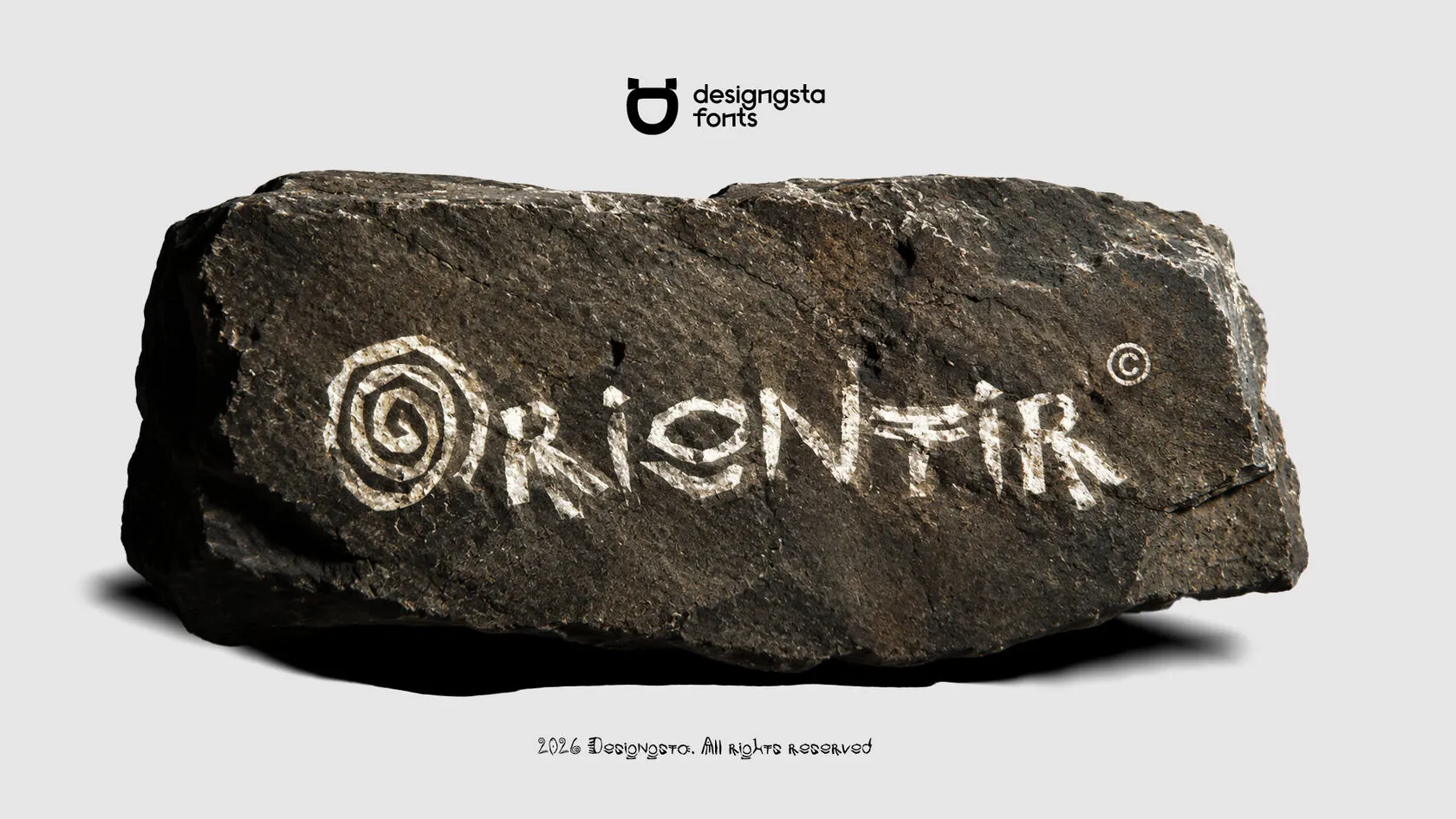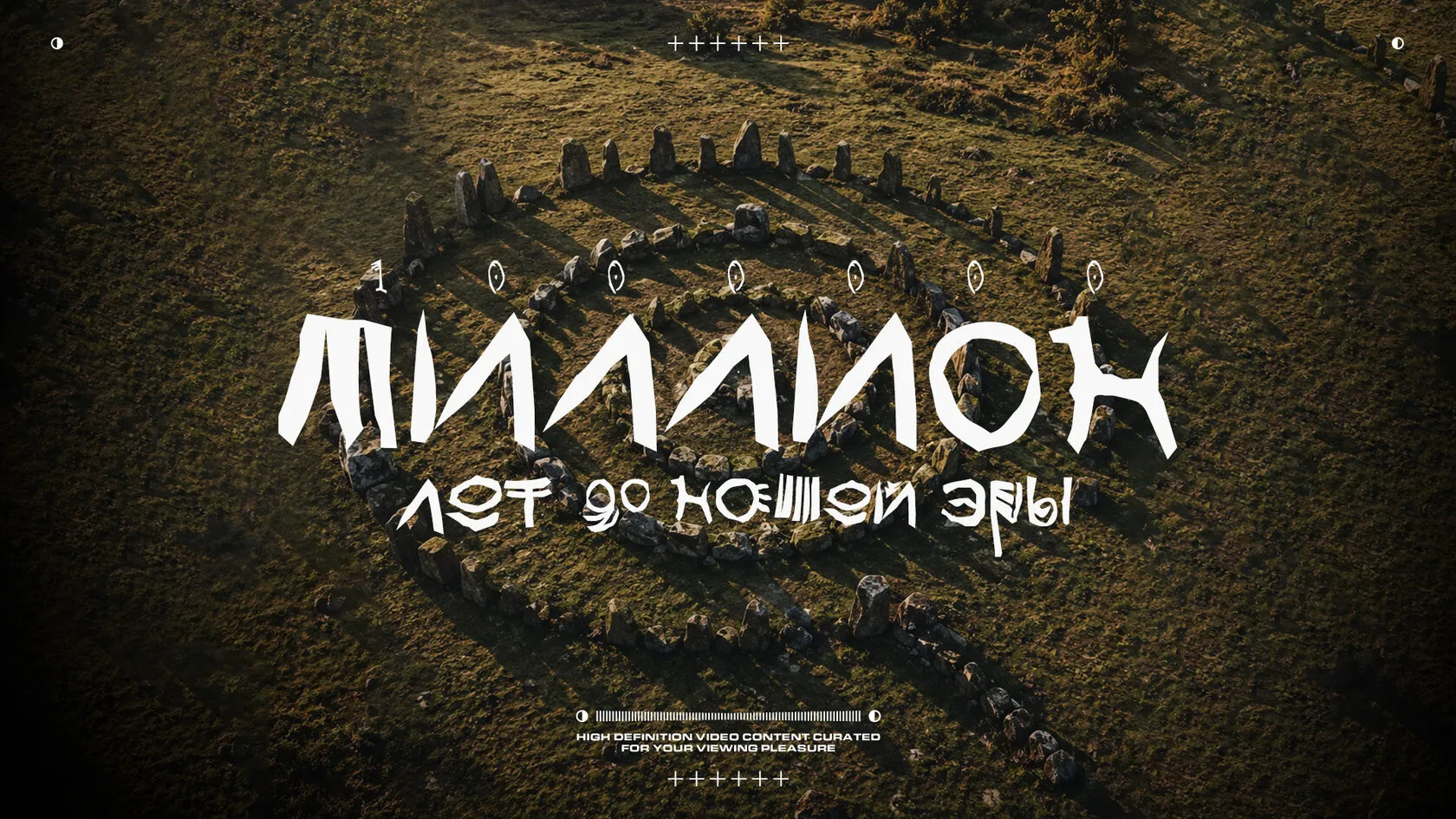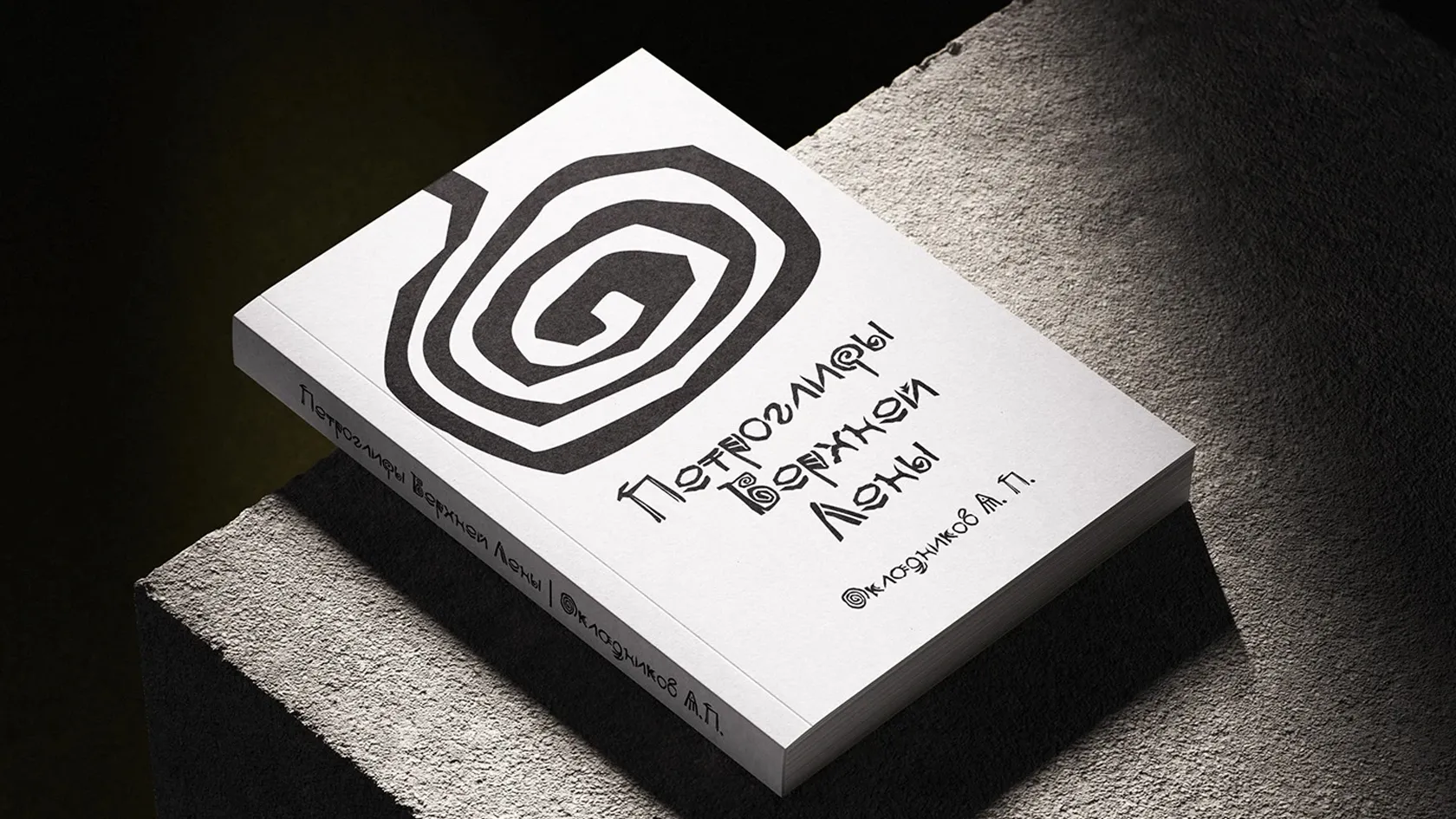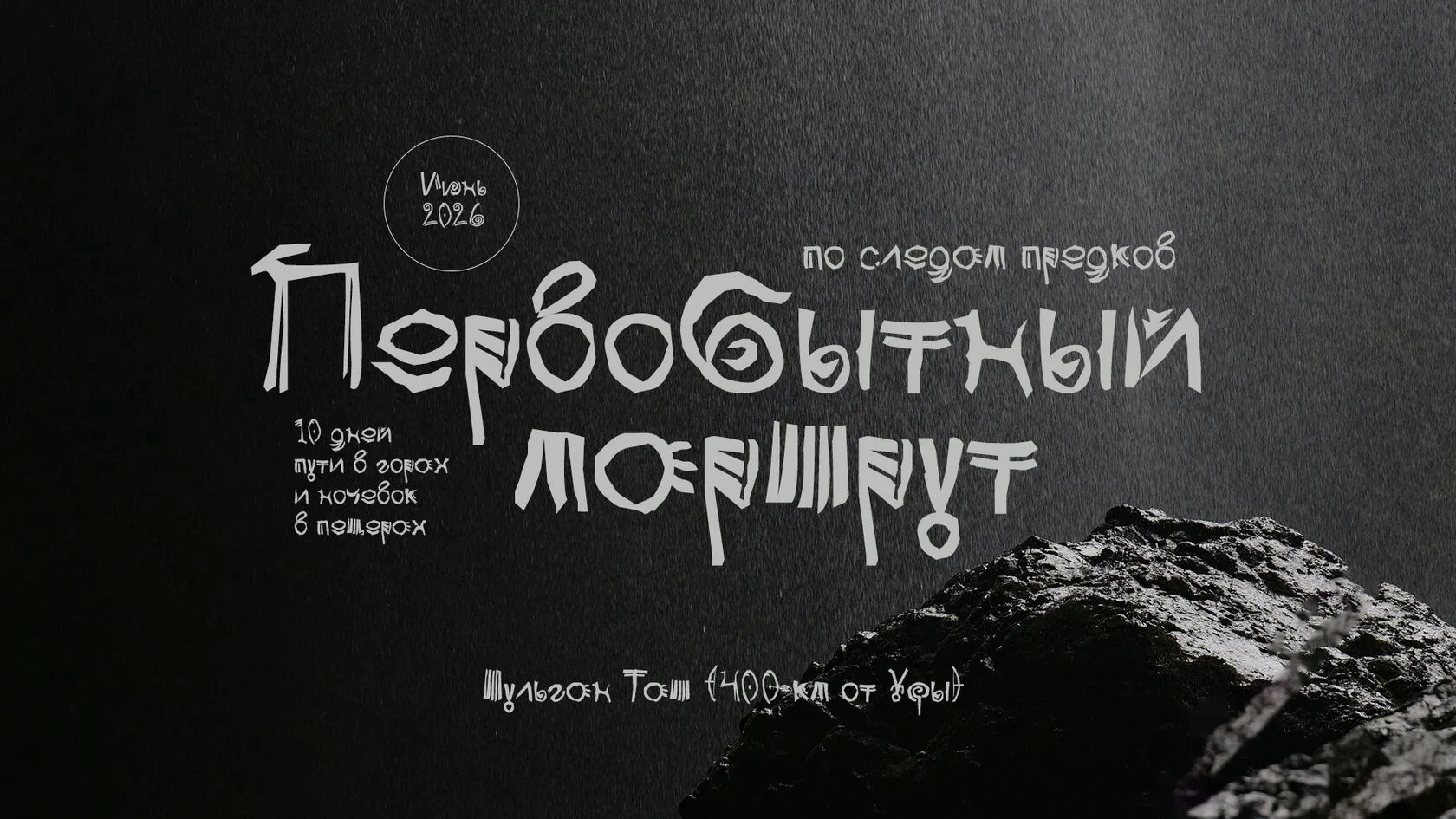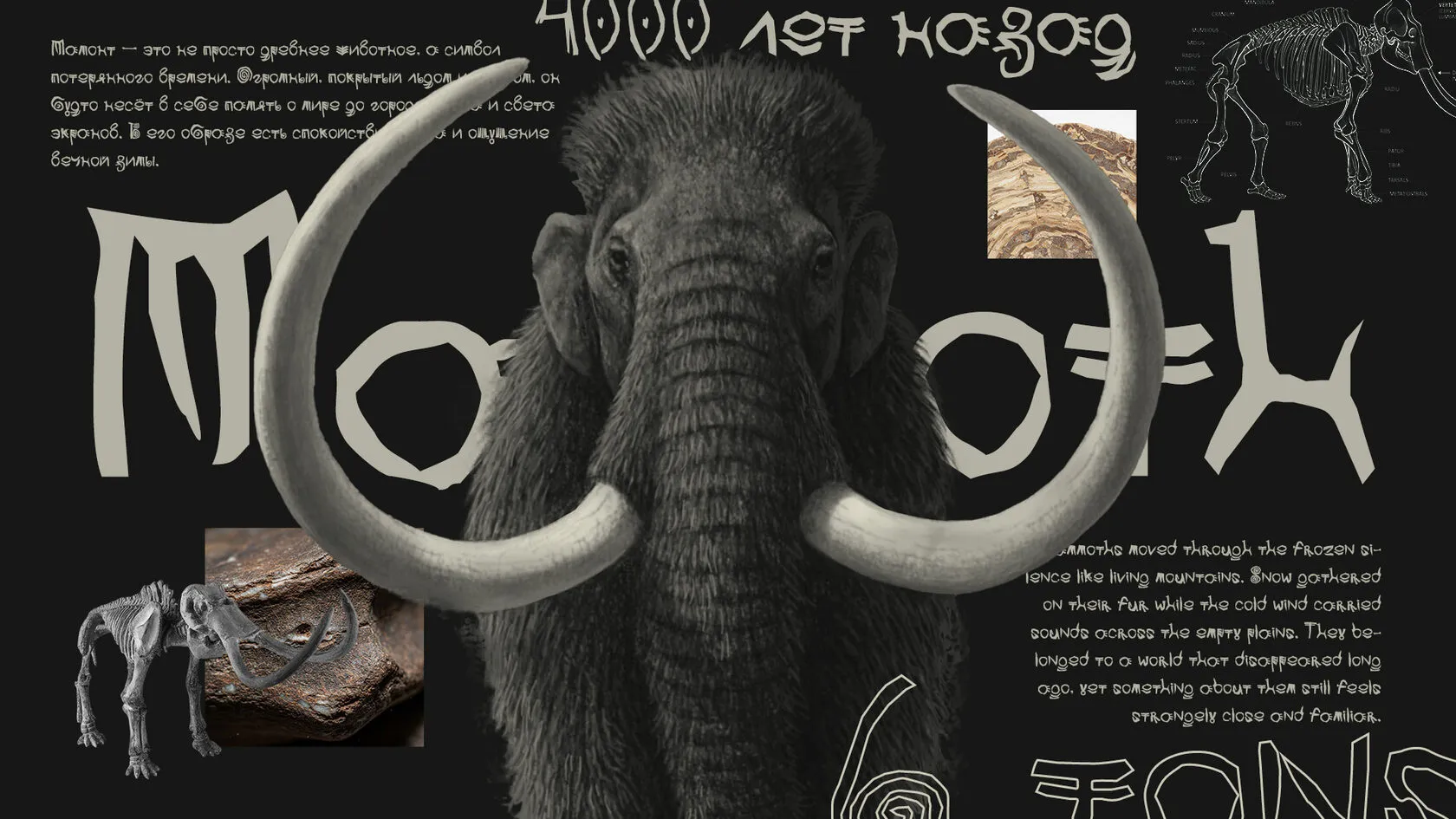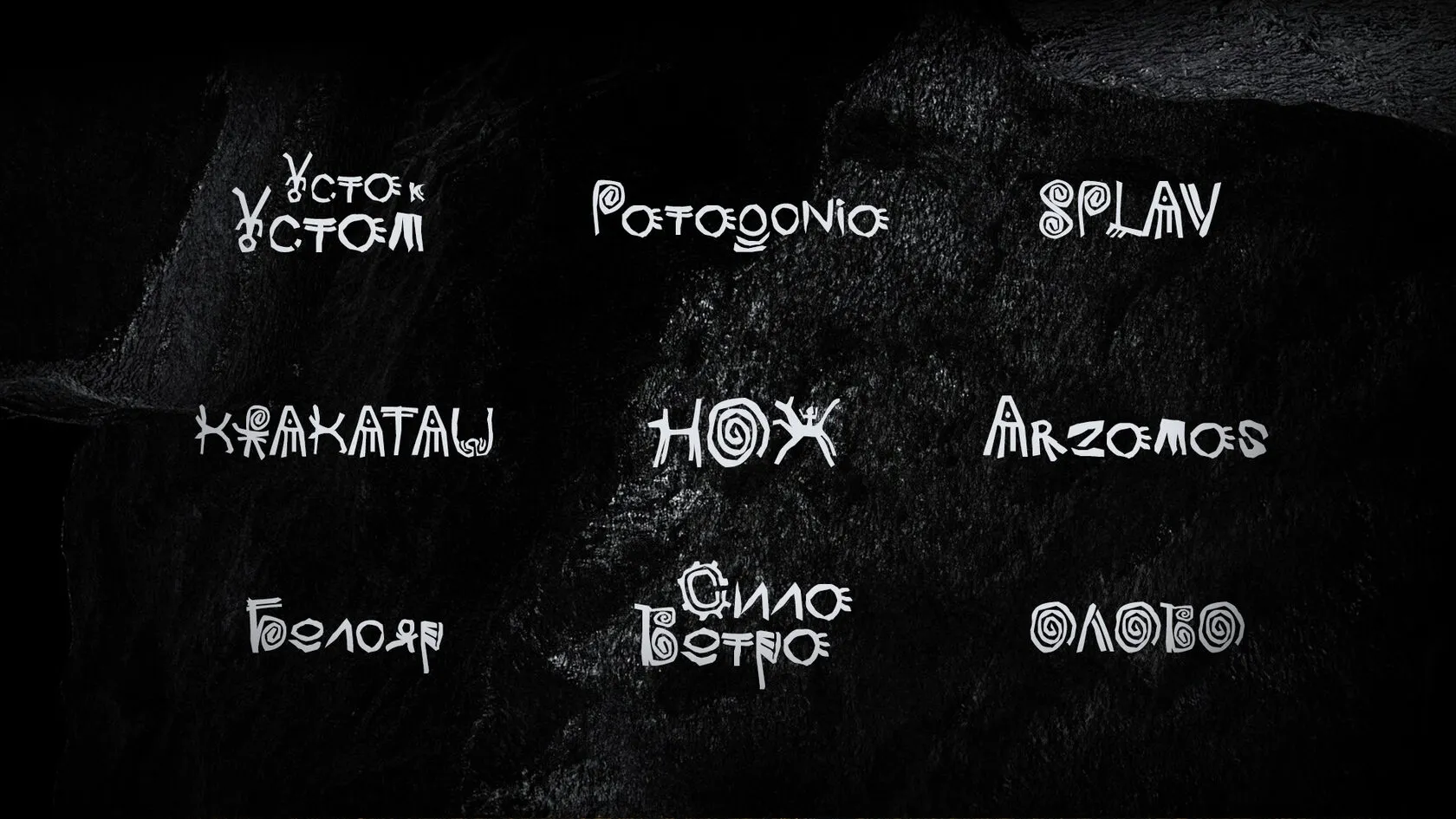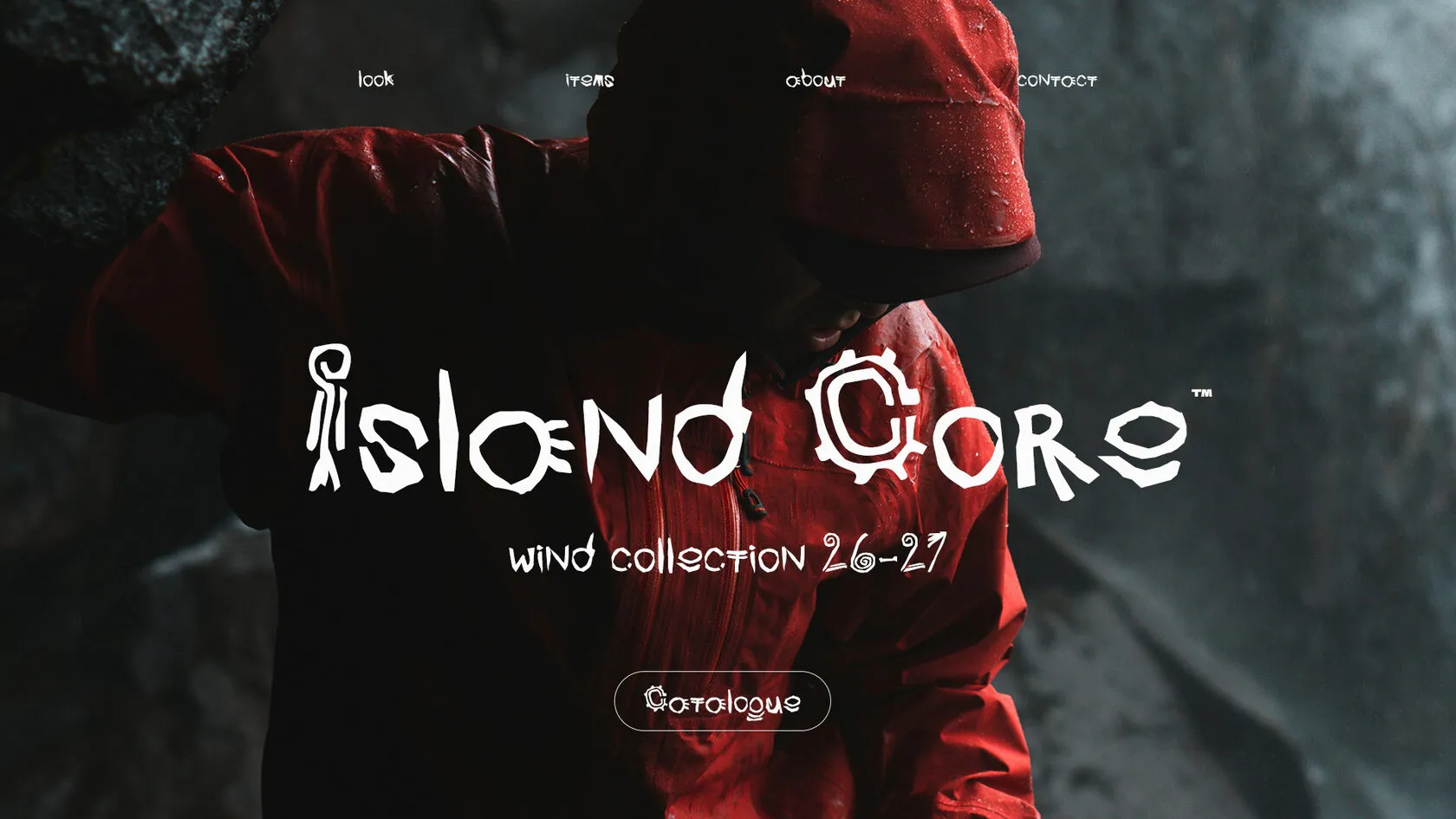
Orientir — бесплатный кириллический шрифт
ORIENTIR© — новый бесплатный шрифт, вдохновлённый древней наскальной живописью, петроглифами и первобытными системами письма разных культур мира.
В процессе создания автор исследовал символы и изображения, обнаруженные в различных регионах — от Алтая и Сулекской писаницы до петроглифов Онежского озера в Карелии. Основной задачей было не просто разработать декоративный шрифт, а передать ощущение древнего ориентира — следа человеческого присутствия, сохранившегося на камне сквозь тысячелетия.
Многие символы шрифта отсылают к охотничьим знакам, маршрутам, изображениям животных, солнечным символам и примитивным картам. Благодаря своему характерному визуальному языку ORIENTIR© особенно хорошо подходит для заголовков, логотипов, постеров, обложек, туристических проектов, археологических изданий, а также материалов, посвящённых путешествиям, природе и исследованию мира.